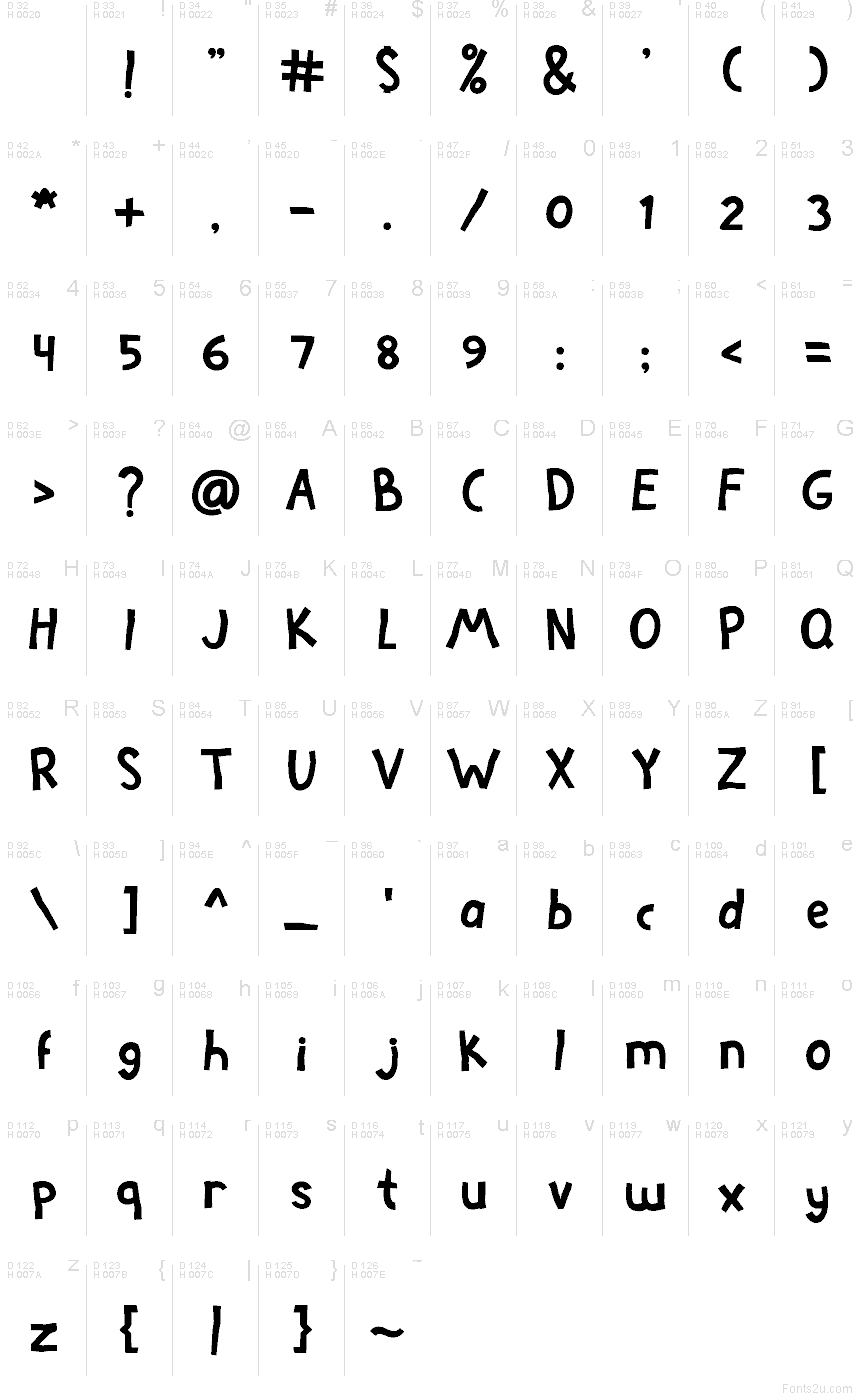
Cafetalk
Tokokooによる「Cafetalk」は、手書きの軽快なリズムと親しみやすい弾みを感じさせる、無料のカートゥーン風ディスプレイフォントです。カフェの看板やコミックのレタリングを彷彿とさせる、ふっくらとした曲線的なフォルムが特徴です。全体的にソフトで少し不規則なリズムがあるため、きっちりとしたフォーマルな印象よりも、カジュアルで親しみやすく、少し茶目っ気のあるデザインに仕上がっています。
パッケージデザインやカフェのブランディング、子供向け書籍のカバー、ポスターのタイトル、メニューなど、このリラックスした雰囲気を活かしたいシーンに最適です。無料フォントですので、SNS用のグラフィックやタイトル画像、短いロゴタイプのデザインにも適しています。すっきりと整いすぎず、会話をしているような温かみのある、大きくて丸い文字をお探しの方におすすめです。